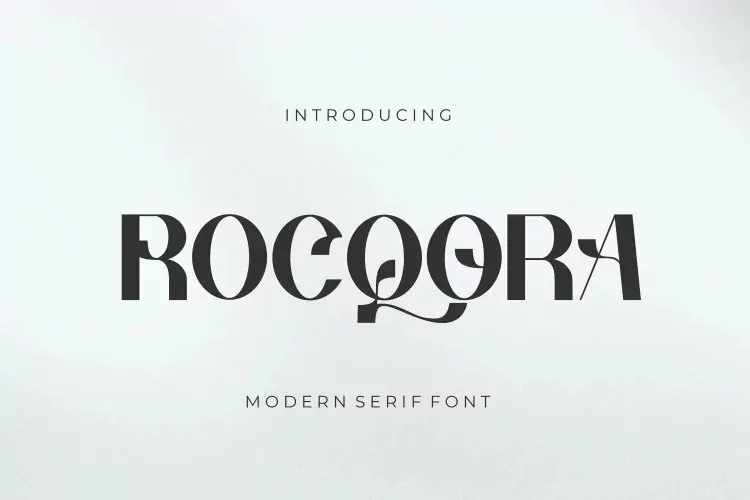
Rocqora Font
A Rocqora Font é uma nova família de fontes sans-serif criada pelo designer Rvandtype. Ela traz suporte alternativo que adiciona diversidade e interessância aos seus projetos, tornando-os únicos. Com um estilo elegante e divertido, a Rocqora é perfeita para criar logos, marcações, convites, design de papelaria, designs de casamento e postagens nas redes sociais. Suas linhas leves e suas formas curvadas suaves oferecem uma abordagem moderna e alegre aos trabalhos gráficos que usa esta fonte. Sem dúvida, ela é ideal para qualquer tipo de projeto visual em busca de estilo e personalidade.